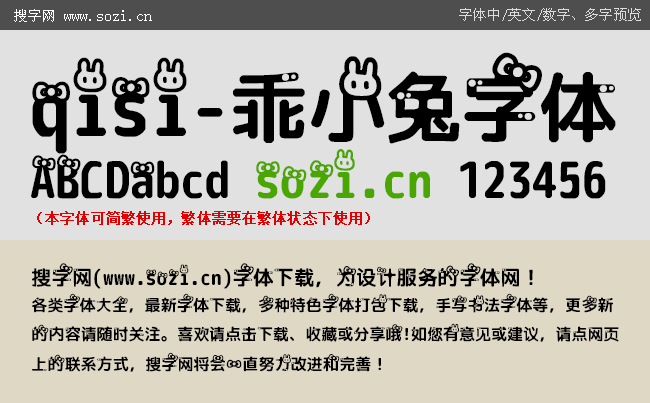
乖小兔字體
搜字網(wǎng)給大家提供一款乖小兔字體手機(jī)中文字體下載。這款手機(jī)字體是在粗圓體字體為原形,筆畫間點(diǎn)綴了可愛的小兔等卡通圖案。在具備粗圓字體醒目清晰端正的風(fēng)格同時(shí),卡通味也特別濃,是一款非?蓯鄣目ㄍㄗ煮w,特別適合喜歡手機(jī)字體個(gè)性一些的朋友在手機(jī)上安裝使用。